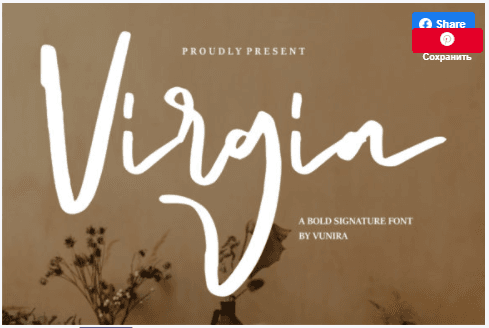
Virgia Font
Virgia - это стильный и аккуратный рукописный шрифт, излучающий элегантность и класс. Этот шрифт был специально разработан для тех, кому нужен красивый и освежающий вид своего дизайна.